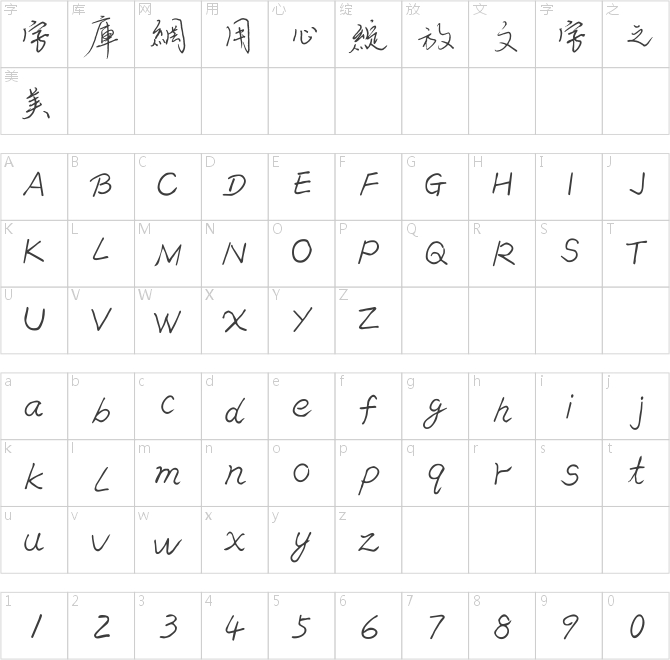
字体名称: 腾祥巧巧手迹繁
此款字为腾祥巧巧手迹。书写一气呵成,独具作者自己的风格,无拘无束具有不同的视觉效果,用于正文更体现出手写自然之感。
腾祥巧巧手迹繁字体TTQiaoQiaoF字库是一款让人赏心悦目、百看不厌的中文字体,适合各类广告和产品包装设计应用,字体大小10.04MB,格式为ttf字体,上传用户是青柠檬,作者/版权方为腾祥字库